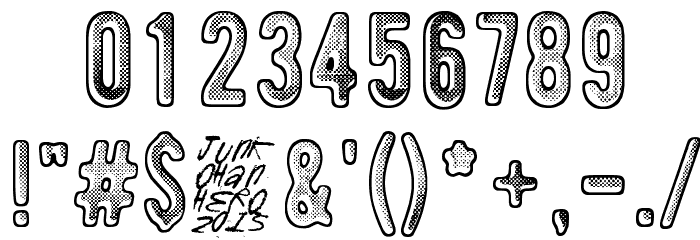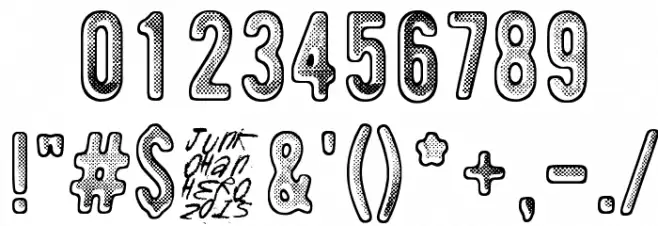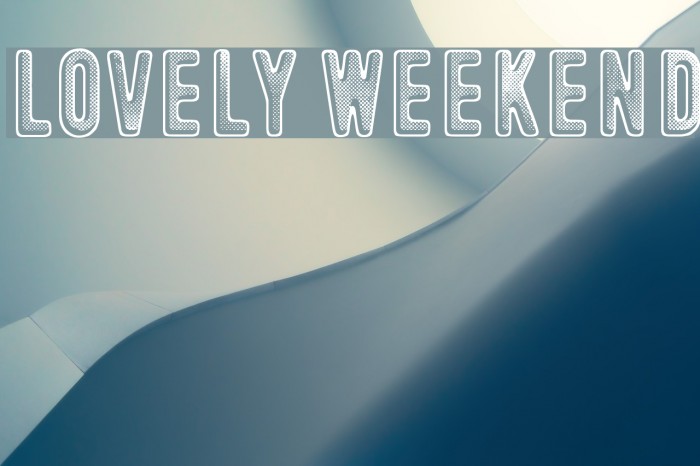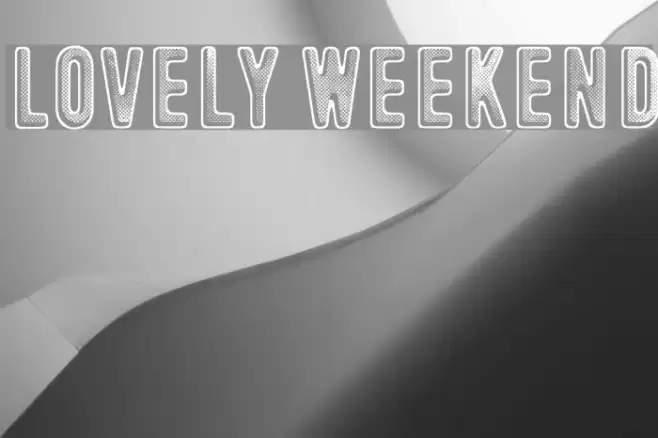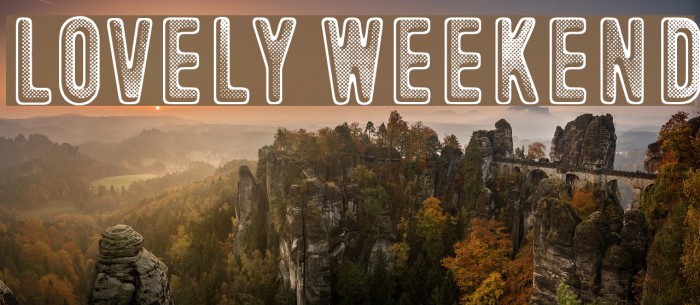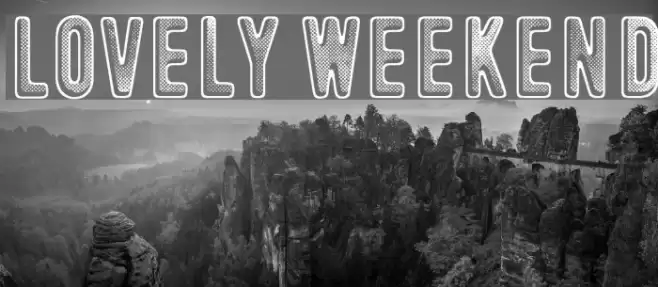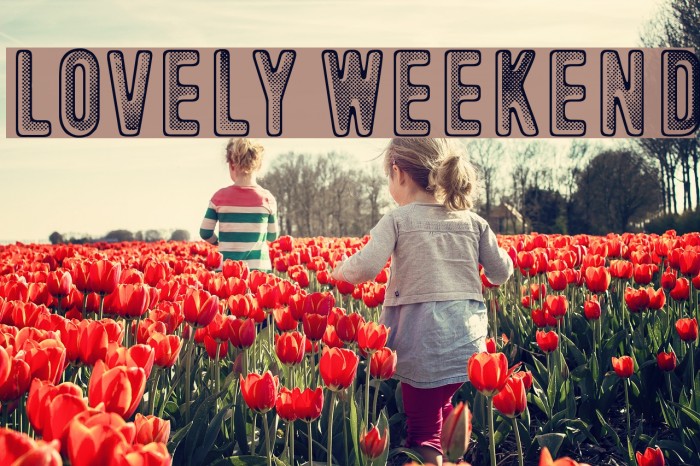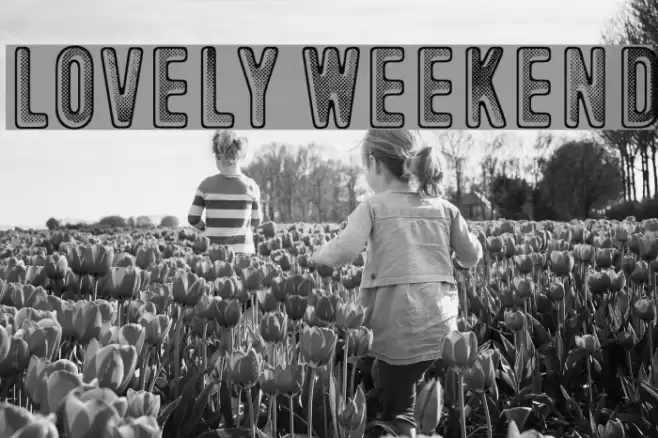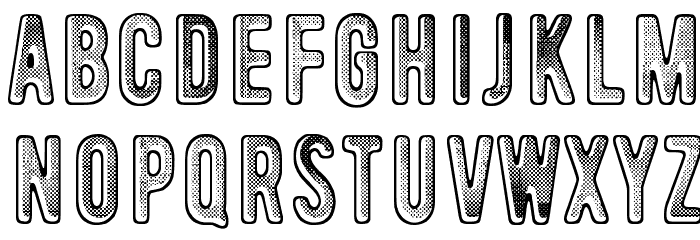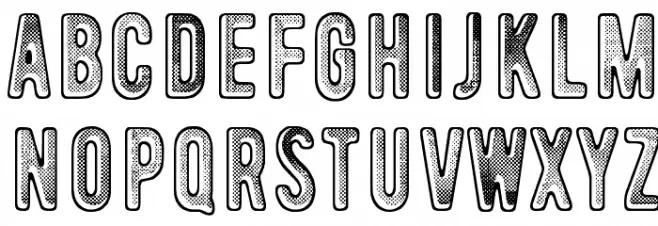
Lovely Weekend Font
| Stile generale | Modern, Decorative |
| Progetti proposti | Ideal for posters, children's books, playful branding, and event invitations. |